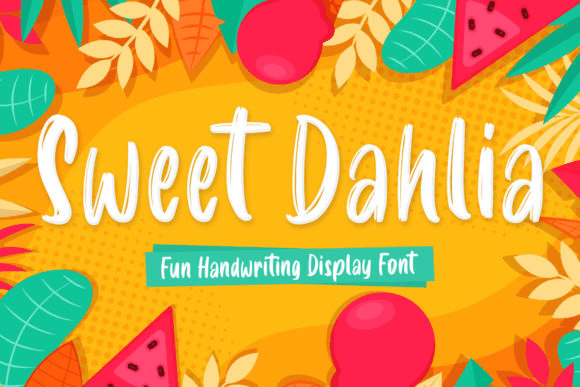
Название: Sweet Dahlia Font
Sweet Dahlia - это шрифт с игривым дисплеем, созданный с помощью пера кисти. Красивый и универсальный, этот шрифт мгновенно станет вашим лучшим выбором для широкого спектра творческих идей!